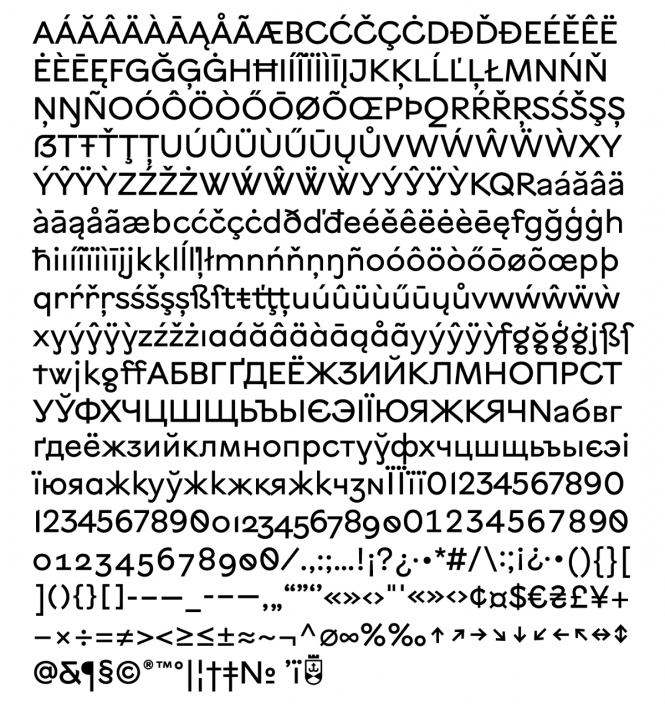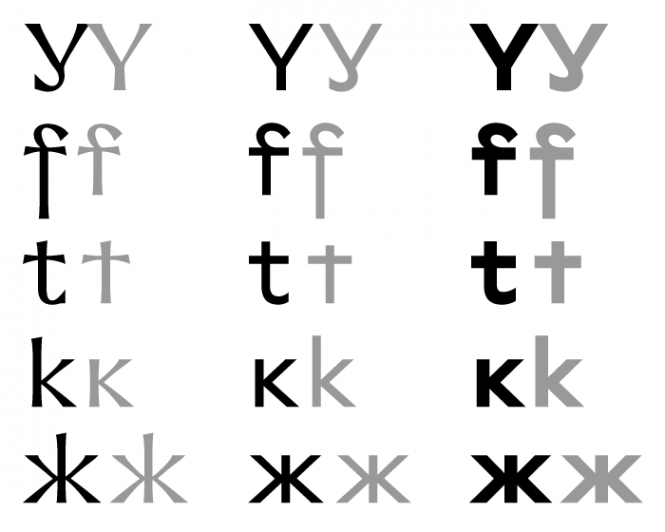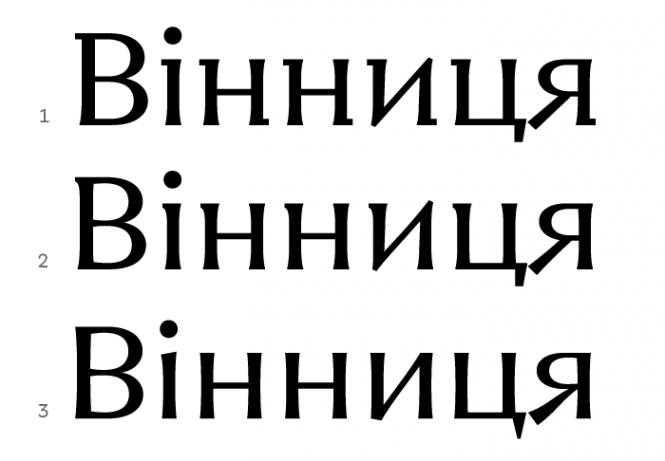
Айдетика від Fedoriv: дизайнер розповів, чому розробив саме такі шрифти для Вінниці
• Шрифтовий дизайнер Дмитро Растворцев, який на замовлення компанії Fedoriv, займався розробкою вінницьких шрифтів, розповів чому шрифти так виглядають.
• Дизайнер зробив на замовлення Fedoriv шрифтову пару карбований – некарбований (Vinnytsia Serif та Sans).
Привіт! Днями Вінницька міськрада оприлюднила бренд міста. Розробляла айдентику компанія Федорів, а я на їх замовлення робив шрифти.
Проект оказавсь примітним, цікавéньким, так шо вирішив розказати, що да як. Писати много буков у фб трохи незручно — так отето як порядочний зарегавсь на Медіумі і пишу еті строкі. Текст спеціалізований, але, маю надію, знайде свого читача.
Шрифти Vinnytsia Serif та Sans
Власне, для Вінниці я зробив шрифтову пару карбований – некарбований (Vinnytsia Serif та Sans), тому розкажу за свій шмат.
Починали шрифт з напису Вінниця. Ну, логічно: напис назви міста— тут річ найвідповідальніша, і танцювати варто звідсіля.
Перші проби карбованого шрифта
За попередніми прикидками макету, шрифт мав бути середньої насиченості (жирності).
Стереотипні локально-українські асиметричні карби (1–2), я так зрозумів, звужували галявину комунікації і врешті прийшли до більш «прозахідного» варіанту — шрифту з ледь помітними карбами чи то пак, потовщеннями на кінцях штрихів (3).
Ледь помітний карб (засічка) шрифта Vinnytsia Serif
Такі недо-карби відомі з давніх давен і, можна сказати, добавляють літерам урочистості, витонченості і історизму.
Ранньохристиянська табличка, Помпеї, I ст.
Декоративні алфавіти. Грегоріус Бок, Німеччина 1510-ті.
Фрагмент напису на фасаді будівлі. Фото: David Quay.
Також такі потовщення основних штрихів на кінцях (вертикальних палок) можна знайти і в кириличній традиції, і в українських класиків.
Актова книга магістрату, 1652.
Ескіз шрифту. Василь Хоменко, 1965.
Лого затвердили. Рухаємось далі.
Вирішили, що для ідентифікації міста, потрібен карбований і некарбований. А некарбований — у двох накресленнях: звичайному (Regular) і жирному (Bold). Ну, так щоб і заголовок, і підзаголовок і основний текст можна було набрать — по красоті. Карбований можна кучерявий, а некарбований мав працювати і в дрібних кеглях, тому без ізлішеств.
Не суперсім’я Гардіан, конешно, але хоть якийсь мені розвиток: давно облизувавсь зробить системне рішення sans−serif, та все руки не доходили. А тут — і карти в руки.
Як казали греки в XXI вєкє, композиція будується на: контрасті, нюансі і подобі. Типографійний контраст нам би давав ще один шрифт — Display, а Sans і Serif мали звучати в унісон (схоже, але з нюансами).
Vinnytsia Display, Vinnytsia Serif та Vinnytsia Sans
(Цією картинкою я трохи забігаю наперед, але шоб було зрозуміла модель майбутнього результату.)
Передививсь прислані референси-мудборди хлопців з Федоріва, помоніторив тренди шрифтобудування. Натхнувсь. Взяв зошит, трохи поупражнявсь. Йти по накаканому путі, копіюючи існуючі прототипи, некомільфошно, так шо старавсь йти небитим шляхом, пропускати через себе. Звісно, всьо уже было — це понятно.
Ескізи Вінницьких шрифтів
Без старого нема нового. Щоб зробити нове — треба старе з’днати в новій послідовності. З такими переконаннями я сів за роботу, пробуючи схрестити бульдога з носорогом. Хотя, мабіть, це громко сказано. Скажем тихіше: бульдога з хортом. Даже так: бульдога і хортúнею (щоб зберегти фемінітивну повістку дня). Чи хортúцею?
Оцих друзєй, коротше:
Виразні риси шрифтової сім’ї Vinnytsia
В результаті генної інженерії шрифти унаслідували від мами граціозність, вишуканість, виразні форми, а від тата велику голову, широку кость і крепке стояння на ногах. Неправильний прикус— тоже папин.
Звучанню в унісон, по ідеї, мав сприяти спільний кістяк. Ну, і однакові висоти виносних та ріст рядкових. Що я і застосував:
Айдетика від Fedoriv: дизайнер розповів, чому розробив саме такі шрифти для Вінниці, фото №12 на сайті 20minut.ua
Лінії висот елементів шрифтів (вгорі) та спільний кістяк (внизу, пунктиром) сім’ї Vinnytsia
Ознакою характеристики шрифта є пропорції — співвідношення ширини й висоти букви, висота талії (середньої лінії).
Айдетика від Fedoriv: дизайнер розповів, чому розробив саме такі шрифти для Вінниці, фото №13 на сайті 20minut.ua
Ознаки шрифтів: ширина, висота середньої лінії.
Як визначили ті ж давні греки (започатківці загальноєвропейської культури ж), букви складаються з трьох базових елементів: круг, квадрат, трикутник. В вінницьких шрифтах я намагавсь якнайближче наблизитись до геометрично правильних фігур, мінімально корегуючі оптику. Тому шрифти мають дещо широкі пропорції в порвінянні з середньою температурою по лікарні. О — круг-круг, H — майже квадрат, А — близька до рівностороннього трикутника, ну і так далі.
Айдетика від Fedoriv: дизайнер розповів, чому розробив саме такі шрифти для Вінниці, фото №14 на сайті 20minut.ua
Порівняння базових літер шрифта Vinnytsia Sans Bold з простими фігурами
А от де талію будем дєлать — тут я прислухавсь уже не до греків, а до варягів конструктивізму. Долой золотоє січеніє, дайош тупо поровну! Баухауз-Юголеф! Коротше, середня лінія в Вінницьких шрифтах знаходиться на геометричній середині, а не на оптичній, як це часто буває. Але не завжди):
Айдетика від Fedoriv: дизайнер розповів, чому розробив саме такі шрифти для Вінниці, фото №15 на сайті 20minut.ua
Порівняння висоти середньох лінії шрифтів
Так, вінницькі шрифти мають трохи широченькі пропорції, а із-за висоти талії букви — масивний верх. Но под’опитні бульдохортипам’ятають, хто батон в будку крошить:
Айдетика від Fedoriv: дизайнер розповів, чому розробив саме такі шрифти для Вінниці, фото №16 на сайті 20minut.ua
Вальтер Ґропіус, 1923. // Адольф Страхов, 1931
Щоб рисунок набору кирилицею і латинкою були більш схожі, я використав нетипові, але спільні рішення елементів: Y повторює У, к жмають щогли, t f — довгі горизонталі (як у т). Але нетипові в кучерявому Serif — в основному сеті, а в попроще-Sans — як альтернейти.
Айдетика від Fedoriv: дизайнер розповів, чому розробив саме такі шрифти для Вінниці, фото №17 на сайті 20minut.ua
Основні (чорним) і альтернативні (сірим) літери з нетиповими рішеннями елементів.
Кстаті, не така це вже й отсєбятіна, якщо понишпорить в архівах.
От пожалуста: щогласті:
Айдетика від Fedoriv: дизайнер розповів, чому розробив саме такі шрифти для Вінниці, фото №18 на сайті 20minut.ua
Гарнітура Хоменківська, перший і єдиний металевий складальний шрифт українського автора. Василь Хоменко, кінець 196о-х. // Козацький скоропис, 1615. // Українська абетка, Георгій Нарбут, 1917. // Гарнітура Пальміра, Словолитня Осипа Лемана / Ingeborg Antiqua, Фрідріх Клейкенс, 1909.
Зубасті:
Айдетика від Fedoriv: дизайнер розповів, чому розробив саме такі шрифти для Вінниці, фото №19 на сайті 20minut.ua
Eccentric Egyptian, 1900-ті. // Raisonné, Benjamin Critton, Colophon Foundry, 2010. // GT Haptik, Reto Moser and Tobias Rechsteiner, Grilli Type, 2009.
Ви ж в курсі, що Запорізькі козаки — вони добрі люди. Під Зборовом в 1649-му дали люлєй коронним військам, заключили мир, оформили пансіон. А потім ще й під Вінницею добавили. Гріх не згадать звитяжні часи.
Звитяжні:
Айдетика від Fedoriv: дизайнер розповів, чому розробив саме такі шрифти для Вінниці, фото №20 на сайті 20minut.ua
Титул Реєстру Війська Запорізького, 1649
Обернеться, поцілує — Зззлипаються губи)
А в Галицько-Волинській державі, оказується, писали латиною. Ніколи раніше не приходило в голову. Так би й жив неуком, якби не цей проект).
Айдетика від Fedoriv: дизайнер розповів, чому розробив саме такі шрифти для Вінниці, фото №21 на сайті 20minut.ua
Документ Галицько-Волинської держави, перша пол. XIV ст
Конструкції f r несуть відбиток середньовічних готичних шрифтів, ровесників Вінниці, та старих гротесків епохи розквіту залізниць та цукрозаводчиків.
Готичні:
Айдетика від Fedoriv: дизайнер розповів, чому розробив саме такі шрифти для Вінниці, фото №22 на сайті 20minut.ua
Фрактура, Wolfgang Fugger, 1533 // Flinsch Halbfette Frankfurter Fraktur, 1911 // Grotesque №8, Stephenson Blake, 1898–99 // NG Grotesque, Colophon Foundry, 2014
Хууух. Заморивсь уже, чесно кажучи, скани шукать. Шось я піддивлявся у минулих майстрів, шось у сучасних, шось малював по пам’яті чи «з голови».
Недавно сплив у профільній спільноті термін «растворцевська у». Зараз уже й не згадаю, звідкіля вона (у-хромосома) така взялась. Ну, хай і так: нада ж уже і в аннали щемиться))
А всі бульдохорти врешті получились такі:
Айдетика від Fedoriv: дизайнер розповів, чому розробив саме такі шрифти для Вінниці, фото №23 на сайті 20minut.ua
Vinnytsia Serif
Айдетика від Fedoriv: дизайнер розповів, чому розробив саме такі шрифти для Вінниці, фото №24 на сайті 20minut.ua
Vinnytsia Sans Regular
Айдетика від Fedoriv: дизайнер розповів, чому розробив саме такі шрифти для Вінниці, фото №25 на сайті 20minut.ua
Vinnytsia Sans Bold
В шрифтах — джентльменський набір цифр (маюскульні, мінускульні, табульовані), альтернативні знаки, лігатури, чутлива до регістру пунктуація, навігаційні стрілочки, нове лого Вінниці. Можна набирати тексти європейськими мовами на базі латинки та українською, білоруською, російською.
А ще — думки спеціально обучених людей (дуже дякую їм):
К О М Е Н Т А Р І
Айдетика від Fedoriv: дизайнер розповів, чому розробив саме такі шрифти для Вінниці, фото №26 на сайті 20minut.ua
Ігор Дудник, історик мистецтва, дослідник теорії та історії шрифтової графіки В сучасному графічному дизайні, практично у будь якій-роботі, прийнято вживати два, найпоширеніші, типи шрифтів: карбовані (серифові) та некарбовані (безсерифові). Першими зручно набирати великі масиви тексту, другі ж вживаються, переважно, для акциденції. Перші мають півтисятолітню історію, другі з’явилися якихось сто років тому, але в сучасних шрифтових родинах, обов’язково наявні обидва типи, літери яких, поєднані спільними графічними ознаками та конструктивними особливостями. Такою є і шрифтова гарнітура Vinnytsia, що має в собі дві, основні, складові: Seif та Sans. Шрифт Vinnytsia Serif карбований — він має ледь намічені серифи, які більше виглядають як певні потовщення на кінцівках основних штрихів. Подібне рішення було популярним у Європі в другій половині ХХ ст., але і на українських землях має давню традицію. Подібні серифи ми можемо побачити у кількох українських друкарських шрифтах XVII ст., або у нереалізованому в металі некарбованому шрифті видатного українського художника Василя Хоменка.
Айдетика від Fedoriv: дизайнер розповів, чому розробив саме такі шрифти для Вінниці, фото №27 на сайті 20minut.ua
Уставний шрифт стрятнської друкарні Гедеона та Федора Балабанів. Фрагмент сторінки «Служебника», надрукованого у Стрятині, 1604.
Айдетика від Fedoriv: дизайнер розповів, чому розробив саме такі шрифти для Вінниці, фото №28 на сайті 20minut.ua
Василь Хоменко. Ескізи шрифту з ледь наміченими серифами. 1965.
Шрифт New City має чітку геометрію, притаманну без карбованим шрифтам ХХ ст. В Україні подібні шрифти вживалися починаючи з 1920-х рр. шрифтовими художниками Львова, Києва, Харкова. У Вінниці не було дуже інтенсивного шрифтового середовища, з визначних дизайнерів, уродженців цього міста, можна пригадати лише ім’я Олега Карпінського, і про спадкоємність у питанні шрифту міста Вінниці, варто говорити трохи в іншому ключі — особливостей літерних накреслень.
Айдетика від Fedoriv: дизайнер розповів, чому розробив саме такі шрифти для Вінниці, фото №29 на сайті 20minut.ua
Адольф Страхов. Фрагмент плаката. 1931.
Айдетика від Fedoriv: дизайнер розповів, чому розробив саме такі шрифти для Вінниці, фото №30 на сайті 20minut.ua
Олег Карпінський. Шрифт Mellnik. 2007.
Літери шрифту Vinnytsia мають певні родзинки. В першу чергу, варто відзначити букву у, яка апелює до старої кирилівської лігатури ук. Дуже влучним є рішення латинської t, верхівка якої нагадує хрест — елемент, який присутній і у гербі міста. Цікава графіка літери з, що натякає на давню кирилівську z-подібну графему, але тут чомусь відсутній нижній виносний елемент літери, що зменшує динаміку, і затискує цю букву у межах базових ліній. З іншого боку, введені верхні виносні елементи літер к та ж, які, навпаки, якраз додають динаміки загальному мереживу тексту та покращують його читабельність. Вперше, в українському шрифтарстві, цей прийом використав В. Хоменко у 1960-х рр.
Айдетика від Fedoriv: дизайнер розповів, чому розробив саме такі шрифти для Вінниці, фото №31 на сайті 20minut.ua
В. Хоменко. Пряме карбоване накреслення Хоменківської гарнітури. 1964–1967 рр.
Загалом, шрифт має стильний, сучасний, динамічний характер. Разом з тим, присутня і певна апеляція до історичного спадку. Цю складову, бажано було би виявити ще більше, увівши, наприклад графему N, яка використовувалася у давній кирилиці замість Н. Крім того, це надало би шрифтові ще більш помітний європейський присмак, який у Vinnytsia Sans та Vinnytsia Serif, безумовно, простежується і зараз.»
Айдетика від Fedoriv: дизайнер розповів, чому розробив саме такі шрифти для Вінниці, фото №32 на сайті 20minut.ua
Вікторія Лопухіна, графічний дизайнер, каліграф, викладач Коли я вивчала цей шрифт, я відразу згадала і експерименти панфутуристів (українських футуристів) і написи «фолькльорного характеру» на тих історичних таблицях, які ще лишились в місті у вигляді вирізблених «унціально-готичних» написів на соборах. Так, цей шрифт — це еклектика. Форми літер незвичні, іноді здається, що мальовані вони і не художником, а звичайною людиною, яка «так бачить» (наприклад хвіст в у). Цей шрифт — такий собі зріз української історії від середньовіччя до сучасності. Літери живі, вони своїми формами розказують історію цієї землі і це круто. Можна аналізувати, придивлятись і інтерпретувати по-своєму. Форми літер хоч і нагадують історію, але прагнуть у майбутнє, в літер точно європейський присмак, європейський напрямок.
Айдетика від Fedoriv: дизайнер розповів, чому розробив саме такі шрифти для Вінниці, фото №33 на сайті 20minut.ua
Вікторія Грабовська , незалежна шрифтова дизайнерка. Народилася і виросла в Україні, живе і працює в Польщі. Присвячує себе проектам від шрифтового дизайну до досліджень. Її шрифти часто підтримують латиницю і кирилицю. Вікторія співпрацює з такими дизайнерами і шрифтовими студіями, як Darden Studio, Cornel Windlin Studio, Lineto, NORM, Rosetta, Studio Aurèle Sack i Sorkin Type. Вікторія викладає шрифтової дизайн в Художньому університеті в Познані та в School of Form. Шрифти — частина візуального ландшафту. Мене давно цікавить, як шрифт стає елементом конкретного простору, як впливає на наше сприйняття місця, пам’ять про нього. Іншими словами, як впливає на тожсамість місця. Чесно кажучи, для мене шрифт як частина візуальної ідентифікації міста — набагато більш витончений і багатогранний партнер, ніж лого. І до того ж всюдисущий. Думаю, що можна сказати, що шрифт стає голосом міста. Голос Вінниці буде виразним. Шрифти Vinnytsia Sans i Serif побудовані на сміливих конструкціях букв і створюють індивідуальний образ, що запам’ятовується. Два компонента, кирилиця і латиниця, не просто стоять поруч, а впливають один на одного. Відчувається, що при створенні проекту вони розвивалися разом. З моєї точки зору, такі проекти в шрифтовій індустрії, насиченої адаптаціями* дуже потрібні і створюють нові напрямки для дизайну обох писемностей. Для мене цей взаємний вплив цікавий не тільки зі шрифтарської точки зору, але і в більш широкому культурному сенсі. І в контексті тожсамості міста це створює додаткову цінність. Цікава структура шрифтової сім’ї: Sans та Serif побудовані на подібних конструкціях букв. Зв’язок безсумнівно видно і він формує споріднену асоціацію. Але тим не менше в цих конструкціях антиква і гротеск реалізують себе досить індивідуально. Для візуальної ідентифікації така можливість корисна, як з точки зору образу так і функції. Антиква і гротеск створюють дві інтонації. І можуть працювати як разом, так і окремо — реалізуючи різні завдання. Характерні конструкції букв вплинуть на запам’ятовуваність шрифту. Але в в широкому спектрі використання, знайдуть застосування і будуть корисні також більш спокійні конструкції букв (а і у), які автор записав в шрифті як альтернативні знаки. У великих масивах тексту їх більш звична форма буде легше читатися, але загальний характер і ритм шрифту буде присутній. Думаю, що стала би в нагоді також більш спокійніша форма Q, особливо в гротеску, і кирилична У. Гротеск існує в двох насиченостях. Хотілося б, щоб у проекту була можливість розвиватися і з часом у антикви теж з’явилися додаткові накреслення, створюючи можливість побудови більш багатої і функціональної типографійної структури. Адаптація — у даному контексті: додання кирилиці до вже існуючої в шрифті латинської абетки.
Каково?! От, приємно мати справу з інтелеґентними людьми: зчитують всі нюанси і відтінки. Ще й вміють сказать академічним слогом.
Виходить, єсть в шрифтах і Вінниця, і Україна, і Європа, і щось старе, і щось нове, і растворцевська у в конце концов!))
За шо, собственно, і боролись).
P. S. Я ж, до речі, опосля, за порадою Віки Грабовської, включив і нейтралочку для Yу, Q. А після зауважень Ігора Дудника в альтернейтах з’явились додаткові форми Нн та з.
Додаткові альтернейти
ЛОНГ ЛІВ ВІННИЦЯ! ЛОНГ ЛІВ БУЛЬДОХОРТ!